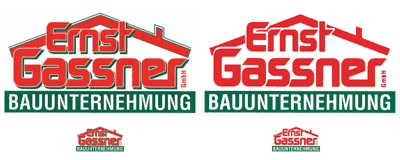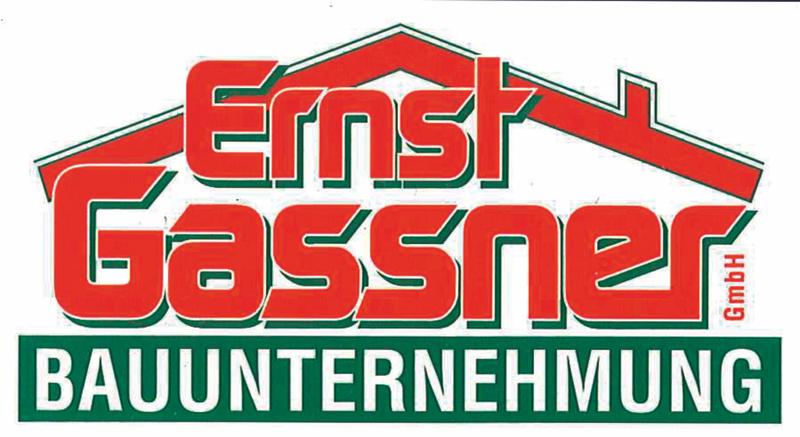
Suche Schrift: Logo Bauunternehmens
Ich muss eine Vektorgrafik aus einem bestehenden Bildlogo erstellen. Dazu würde ich die zwei Schriften aus diesem Logo benötigen (Ernst Gassner und Bauunternehmen)!
Kennt jemand diese Schriften?
Bauunternehmung ist wohl eine Helvetica Bold Condensed und Ernst Gassner sieht selbstgezeichnet aus. Zumindest ist das schneller nachgezeichnet, als wenn man stundenlang eine ähnliche Schrift sucht, die man dann evtl. noch anpassen muss.
Und wenn man schon am Rumzuppeln ist, könnte man auch vorschlagen, die ganzen grünen, feinen Linien im oberen Teil ersatzlos zu entfernen, dann wirkten die Farben meiner Meinung nach direkt freundlicher:
Wenn man die Enden der Buchstaben nicht ganz so spitz abschneidet, könnte man auch der Typografie die Schärfe nehmen und eine modernere Version des Logos erzeugen, die das alte Logo in Ehren hält.